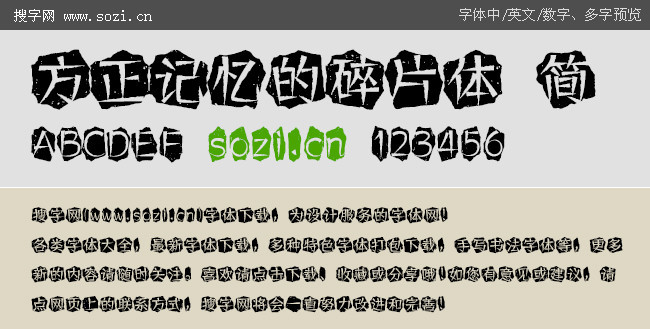
方正記憶的碎片體-簡(jiǎn)
搜字網(wǎng)提供一款方正記憶的碎片體中文藝術(shù)字體下載,將“記憶的碎片”制成一套電腦字庫(kù),貫穿了記憶從搜索、挖掘、整理、修復(fù)、重構(gòu)的全過(guò)程,這與文物器皿修復(fù)還原以及殘破碑刻拓片裝裱有異曲同工之妙。字庫(kù)中的每一個(gè)文字,都好像是從石碑上脫落的殘片,甚至能勾起人們拿在手上“把玩”的欲望。作為一款標(biāo)題字,可以和懷舊的相關(guān)題材精準(zhǔn)匹配,引人入勝,有助于更好地實(shí)現(xiàn)內(nèi)容與形式的高度統(tǒng)一。